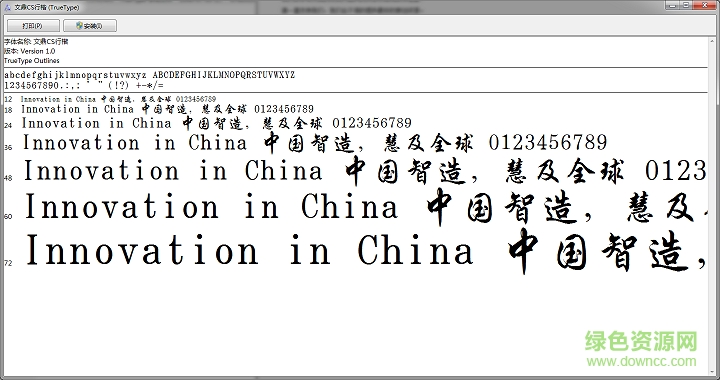
singkaicseg bold gb字體又叫文鼎cs行楷字體,字體辨識(shí)度高,字形規(guī)范美觀,筆畫(huà)連貫,清晰易讀,可應(yīng)用于書(shū)刊、報(bào)紙、廣告、ppt等各個(gè)領(lǐng)域!
【筆數(shù)區(qū)別】
寫(xiě)行楷的過(guò)程中,個(gè)別時(shí)候由于連帶的需要,加上個(gè)別筆畫(huà)的合并、替代和減省,很多筆畫(huà)自然地連在一起書(shū)寫(xiě),筆數(shù)會(huì)比楷書(shū)有所減少。
【用筆區(qū)別】
楷書(shū)的起筆、行筆、收筆等過(guò)程中提筆、頓筆、轉(zhuǎn)筆等運(yùn)用要求嚴(yán)格,書(shū)寫(xiě)要平穩(wěn),有輕重提按、入鋒回筆等具體要求。筆數(shù),筆順,一定的行筆規(guī)則是不可以隨意改變的。
而行楷的用筆則靈活、方便,一般不需要逆鋒、頓筆、停筆等嚴(yán)格的運(yùn)筆,不強(qiáng)調(diào)用筆中更多的提按、筆畫(huà)形態(tài),只要求筆道流暢,使轉(zhuǎn)合理,行筆巧妙。還可以依照書(shū)寫(xiě)者的習(xí)慣而使筆畫(huà)的行筆出現(xiàn)各種變化,甚至依照個(gè)人不同的審美和書(shū)寫(xiě)風(fēng)格去追求或創(chuàng)造出不同的筆道線條。
【筆順區(qū)別】
楷書(shū)的筆順比較固定,先寫(xiě)哪一筆,后寫(xiě)哪一筆,是根據(jù)漢字結(jié)構(gòu)特點(diǎn)加之人們?nèi)粘?shū)寫(xiě)習(xí)慣而總結(jié)出來(lái)的。就一般情況而言,楷書(shū)的筆順是不可以改變的,改變了筆順極容易造成筆畫(huà)書(shū)寫(xiě)不到位,使字形走樣,影響書(shū)寫(xiě)效果。
行楷的筆順不是一成不變的。行楷的書(shū)寫(xiě),根據(jù)實(shí)際需要,個(gè)別地方由于書(shū)寫(xiě)到具體部位時(shí),筆畫(huà)的連結(jié)、縈帶、減省等使字形變化,相應(yīng)的筆順也隨之改變了。有的字中的筆畫(huà)可以先寫(xiě)、也可以后寫(xiě)、但這也只限于一些非主要的筆畫(huà),字中的主筆是要按照書(shū)寫(xiě)順序來(lái)寫(xiě)的。